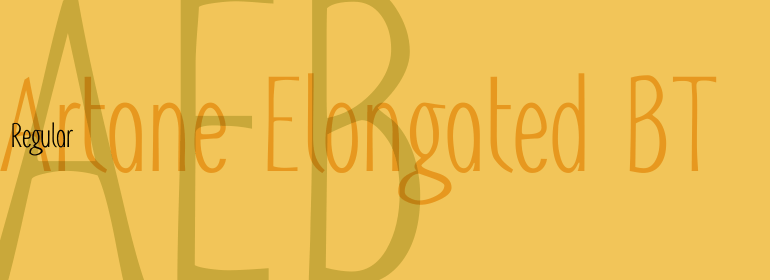
Artane Elongated BT
Artane Elongated BT,这款字体结构工整、笔画清晰,兼顾美观与易读性,适用于标题、正文、海报、包装、LOGO 等多种场景。字形优雅稳定,风格百搭耐看,适配日常排版与创意设计,让文字呈现更舒适、更具质感。Artane Elongated BT一笔一画,皆是细节,以均衡的比例、流畅的线条打造舒适视觉体验,字形端正大气,风格简约现代。无论是商业设计、品牌宣传还是日常排版,都能轻松驾驭,让文字更有格调与力量。Artane Elongated BT字体下载。
字体品牌: Bitstream(Monotype) 设计师:Fahy,Tony 字体分类:无衬线体 字体属性:外文 字符集:Unicode 发布时间: 2018